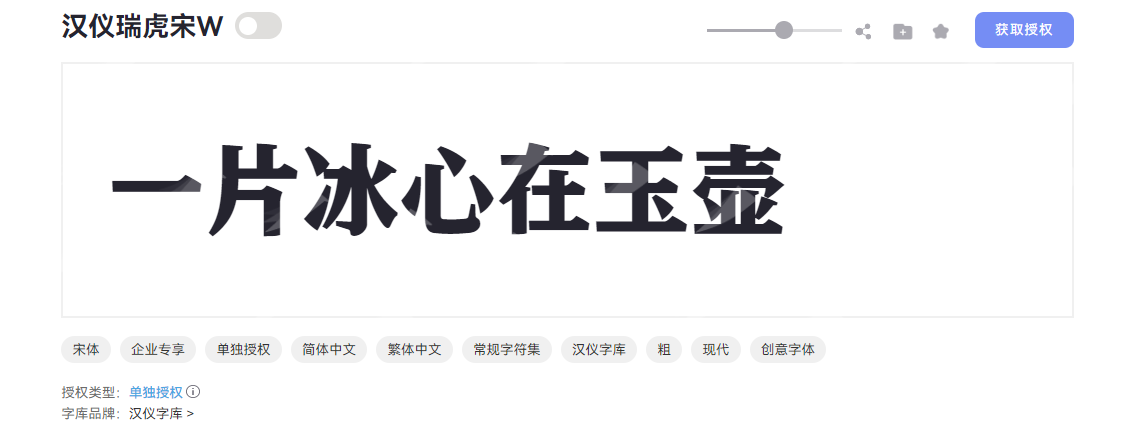
汉仪字库打包下载教程,这 5 款字体设计师必备
汉仪字库是设计行业必备的字体库之一,从老牌经典字体到新锐创意字体,它几乎都是设计师们的首选,真的是宝藏字体!但很多人会卡在第一步,去哪找合规的汉仪字库?怎么安装字体?可以直接商用吗?这些都是老生常谈的问题了,找到一个靠谱的字体资源网站变得至关重要。今天给大家推荐一个设计师必备的字体管理神器——字由,它的字体资源里包含一整个汉仪字库,而且每款字体都会标注清晰的授权方式,绝对是下载汉仪字体的首选工具,同时再给大家附上 5 款设计师常用且好用的汉仪字体资源,绝对让你满意!
二、设计师必备!5 款精选汉仪字库字体推荐
1.汉仪瑞虎宋W
字体类型:宋体
汉仪瑞虎宋 W 是汉仪字库推出的现代创意粗宋标题字体,融合宋体经典基因与当代设计语言,以厚实稳重的笔形与舒展大气的间架结构,彰显独特人文气质。字形方正端庄,重心居中稳定,中宫松紧适度;笔画设计融入精致装饰元素,方头笔画与断开式结构的创意处理,使字体在粗重均匀的笔形中呈现丰富细节,在标题设计中展现出极强的识别度与艺术表现力。
2.汉仪润圆
字体类型:圆体
汉仪润圆是一款精致优雅的圆体家族,总共包含 5 个字重。字体设计之初参考了颜真卿《干禄字书》,字形略宽博,持重舒和而不局促,中宫偏大,照顾用户的阅读体验;字体横竖比例拉开,让粗体看起来不笨拙,笔画变量带些许隶味,给人轻松感。整体风格文艺柔美、精致且优雅。
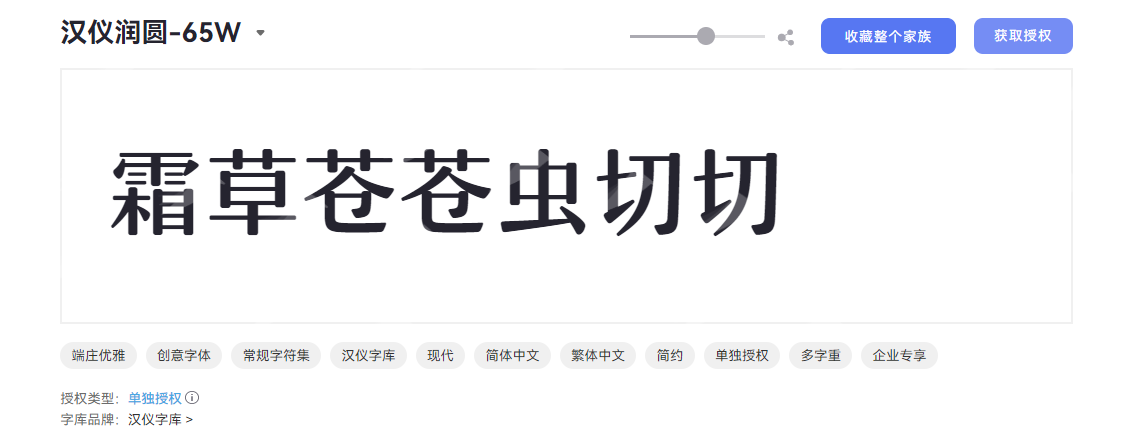
3.汉仪小麦体
字体类型:手写体
汉仪小麦体原本用于绘本漫画中的手写字体,笔画的粗细变化,有漫画一样轻松流动的感觉,字画不分家,设计师的初衷是希望把品味咖啡般的轻松随意休闲的感觉与大家分享。笔画走势自由洒脱,中间会有空隙,模拟了用蜡笔涂画时会产生的质感,视觉上非常舒适自然;每个字符的大小看似不一样,实则都保持在一个隐形的框架里,有序且规整;笔画边缘多采用圆角处理,让字体显得更加柔和。
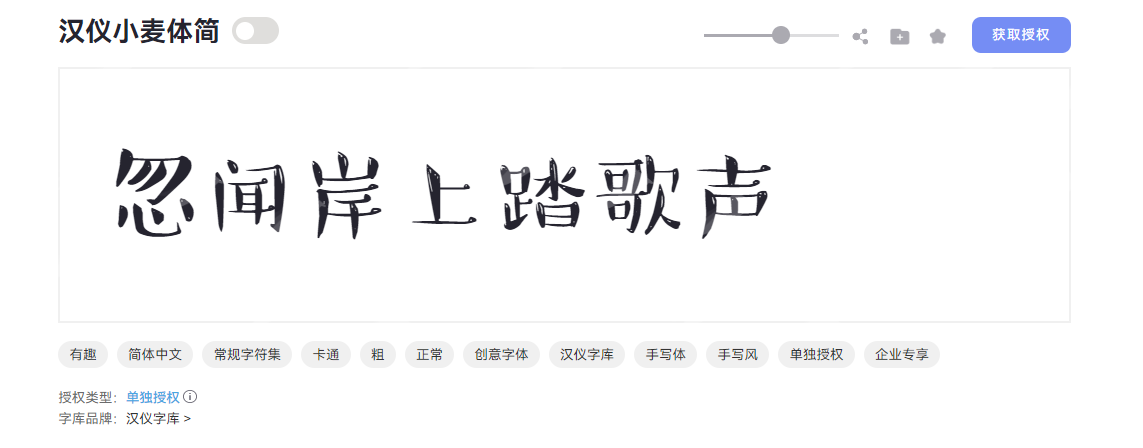
4.汉仪雅酷黑
字体类型:黑体
汉仪雅酷黑是汉仪字库推出的创意黑体,兼具现代感与力量感,以超粗字重打造鲜明视觉记忆点。字形方正稳重,中宫宽博,配合直角方头笔画与独特的笔画断开设计,既保留黑体的端庄大气,又通过平行笔刷般的线条营造出手写质感。字体略高的视觉重心提升字体精神挺拔度,粗细均匀的笔画与断开式结构形成巧妙对比,既强化块面视觉冲击力,又增强小尺寸下的识别性。
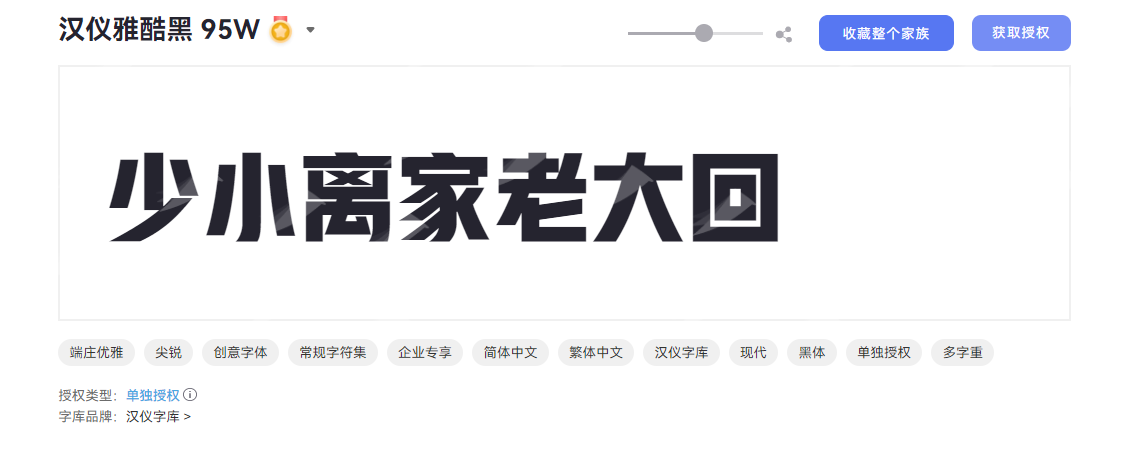
5.汉仪糯米团W
字体类型:创意体
汉仪糯米团 W 是汉仪字库推出的创意卡通字体,以“软糯萌趣”为设计核心,融合手写温度与童趣美学,字重粗实饱满,尽显活泼元气。 汉仪糯米团 W 在字形结构上暗藏巧思:采用扁宽比例,重心居中稳当,中宫宽博舒展,让每个字符都像圆滚滚的糯米团子般讨喜。笔画设计上,圆头笔形搭配末端圆润装饰元素,线条如棉花糖般柔软有弹性,间或点缀俏皮圆点笔形,笔画连接处自然断开,既保留手写的随性,又添几分稚趣。